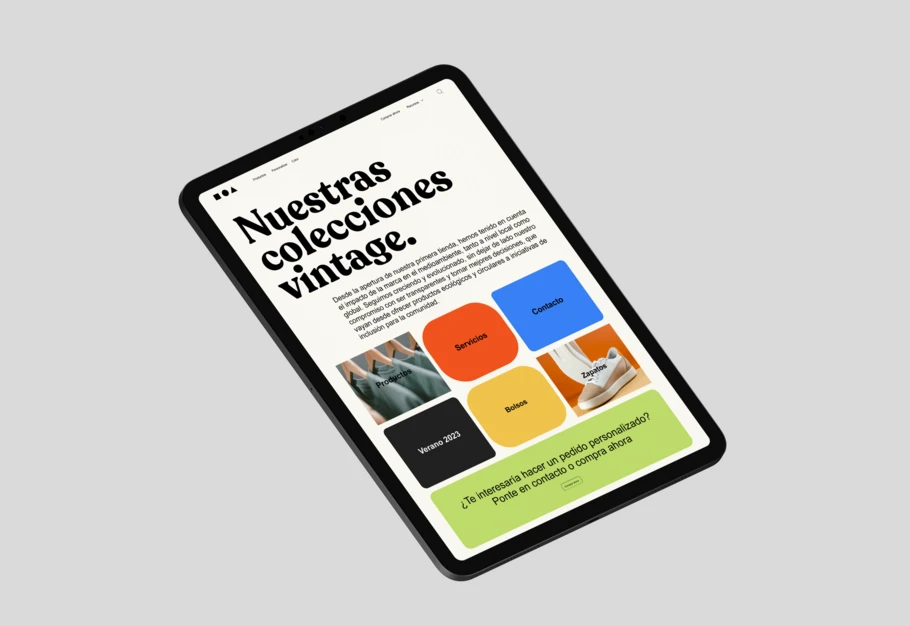
Una imagen impecable: Cinco formas de hacer que tu marca triunfe en la era digital.
¿Tus fuentes de marca funcionan igual de bien en el mundo físico que en la web? ¿Se leen bien en aplicaciones? ¿Y en anuncios de imagen o banners digitales? ¿Qué tal se comportan en entornos completamente nuevos, como el metaverso?
Homogeneizar la presencia omnicanal y la transformación digital de una marca en todas las plataformas es complicado, independientemente de si estás creando una página web, un banner digital, una aplicación, una experiencia de realidad virtual o un nuevo juego en un entorno virtual.
Dado que los consumidores pasan de las pantallas grandes a las pequeñas y viceversa, es vital que las marcas les sigan el ritmo. Las fuentes que eliges marcan la diferencia. Al fin y al cabo, tener una presencia de marca coherente en todos los puntos de contacto ayuda a reforzar la confianza y crea una experiencia de cliente agradable.
Por ello, la próxima vez que debas afrontar un diseño para el mundo moderno, usa esta práctica lista de comprobación para asegurarte de que tus fuentes estén a la altura de la era digital y no tengan ningún problema.
1. Comprueba que sea legible.
Que una fuente sea perfectamente legible en un dispositivo no implica que lo sea en todos. ¿Es molesto? Sí. ¿Tiene solución? Por supuesto. Usar una fuente que sea nativa de una aplicación o ajustar el espacio carácter por carácter hasta que el aspecto sea adecuado en tu aplicación de diseño puede generar faltas de claridad, imprecisiones o incluso hacer que el público desconfíe de la marca. En el mundo digital, los consumidores deben poder leer las fuentes con facilidad tanto en las aplicaciones como en los videojuegos y en los entornos de realidad virtual. Por ello, es fundamental elegir un tipo de letra que haya sido diseñada por manos expertas para funcionar en todos estos formatos.
2. Comprueba que se cargue rápido.
Dado que las marcas conectan con los clientes en el entorno digital, hay un aspecto funcional que debe tenerse en cuenta: ¿cómo afecta a tus tiempos de carga ese tipo de letra gratuita que te has encontrado en algún lugar aleatorio de Internet? Si tienes archivos de fuentes antiguos (que es lo más probable), seguramente te estén afectando negativamente.
Los clientes no están dispuestos a esperar y abandonarán cualquier página web, aplicación o videojuego si tarda demasiado en cargar. Para evitarlo, usa fuentes de proveedores que optimicen el rendimiento de su software. Si tus fuentes están siempre al día desde el punto de vista tecnológico, no tendrás que preocuparte por lo que hay detrás.
3. Comprueba que se reduzca y aumente el tamaño del texto.
Desde los títulos de los sitios web hasta lo que se lee en la pequeña pantalla de un smartwatch, es esencial usar texto dinámico en la experiencia de toda marca digital; es decir, texto que cambie según el diseño o los parámetros. Se trata de algo muy habitual en Web 2, ya que muchos sitios web dinámicos escalan fácilmente en función de si se usan en ordenadores, tablets o móviles. Ahora, es momento de que las marcas piensen en cómo se mostrarán sus fuentes en un panorama más colaborativo y descentralizado, como Web 3 y los entornos de realidad aumentada y realidad virtual.
Por último, si hay algún cambio en un mensaje o concepto, el personal de diseño (u otras personas de confianza que se dediquen a tareas creativas) debe poder hacer que el texto cambie rápidamente. Es algo que ocurre constantemente en los sitios web de noticias, con las actualizaciones de videojuegos o incluso en los sitios de comercios minoristas cuando se preparan para una nueva temporada. En Internet ya no hay casi nada que sea estático, y utilizar una fuente dinámica ayuda a hacer cambios de forma eficiente y ágil, y sin tener que preocuparse porque haya problemas de legibilidad en las pantallas.
4. Comprueba que no haya problemas de visualización.
Otra cuestión sobre la funcionalidad de las fuentes que no puede pasarse por alto es la visualización del texto. Es un asunto complicado, especialmente en lo que respecta al desarrollo de aplicaciones o a la creación de otros recursos digitales que pueden tener caracteres detallados o especiales. Los problemas de visualización suelen implicar que se desactiven las mayúsculas o que los caracteres se reordenen o se muestren con una forma o dirección incorrectas. Esta situación puede ser especialmente problemática cuando se usan fuentes de distintos idiomas. Los equipos de diseño más inteligentes saben ver cuándo hay problemas de visualización y son conscientes de que las fuentes pixeladas y los diseños de mala calidad hacen mucho daño a las marcas. Por su parte, los clientes suelen sentirse confusos y se ven obligados a lidiar con la frustración que generan estos problemas. Por ello, es vital elegir una fuente fiable que incluya un conjunto de caracteres completo y alfabetos sin fisuras que se visualicen correctamente.
5. Comprueba la identidad de marca.
Hasta ahora, hemos hablado sobre aspectos funcionales y creativos que permiten mostrar textos claros, legibles y que se cargan rápido en cualquier dispositivo. Todo esto forma parte de la representación de la marca. Si hay una fuente que se utiliza en materiales impresos, pero que no está optimizada para usarse como fuente web, los equipos de diseño se ven obligados a tomar la difícil decisión de elegir una fuente web que no es idéntica a la impresa. A veces sale bien, y otras es un auténtico desastre. Ofrecer una experiencia de marca incoherente en los ámbitos físico y digital crea una sensación de disonancia en la mente de los consumidores: de forma inconsciente (y a veces también consciente), sienten desconfianza, conectan menos con la marca o se notan menos cercanos a ella.
Para evitar este problema, las marcas pueden elegir desde el principio una fuente que tenga exactamente el mismo rendimiento en los entornos físico y digital, lo que resulta todavía más relevante si tenemos en cuenta que la realidad del futuro será mixta (sí, metaverso, estamos hablando de ti). En resumen: el trabajo de diseño consiste en procurar que no haya fisuras en la experiencia de marca y, para ello, la función de las fuentes es crucial.
Con un programa como este, puedes tirar por la ventana la lista de comprobación que te acabamos de mostrar (bueno, quizá todavía no). En cualquier caso, seguro que sería un placer poder hacerlo. Hasta que lleguemos a ese punto, a continuación te dejamos una versión resumida de lo que debes comprobar con respecto a las fuentes. Para obtener más información sobre Monotype Fonts, visita Monotype.com.
Lista de comprobación de fuentes para productos digitales.
- Legible
- Carga instantánea
- Dinámica
- Nítida
- Conforme con la marca